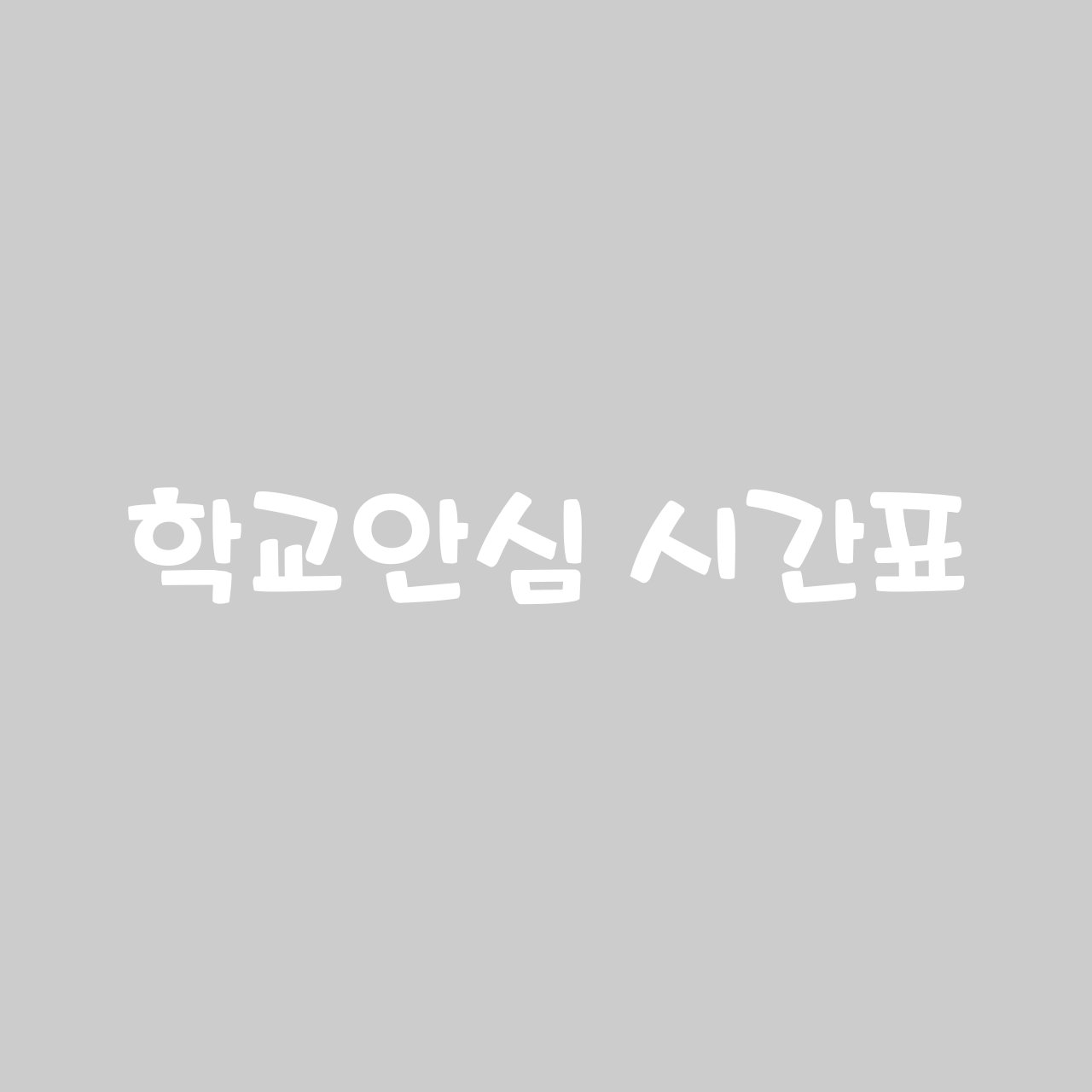
원스토어 모바일POP
슬기로운 폰트 사용을 위해! 원스토어 글꼴 3종은 모바일에 최적화된 서체에요. 누구나 가독성 좋은 모바일 글꼴을 이용할 수 있도록 사장님의 오더에 따라 무료로 널리 배포하고 있죠. 원스토어 글꼴은 안정적이고, 단단한 고딕체 그리고 생동감있는 POP체가 있어요. 원스토어 모바일POP체는 원스토어만의 성격이 담긴 생동감있는 손글씨 서체에요.
- Sans,민부리
- 원스토어 모바일POP / ONE Mobile POP OTF